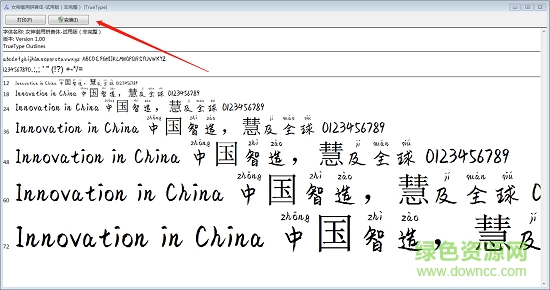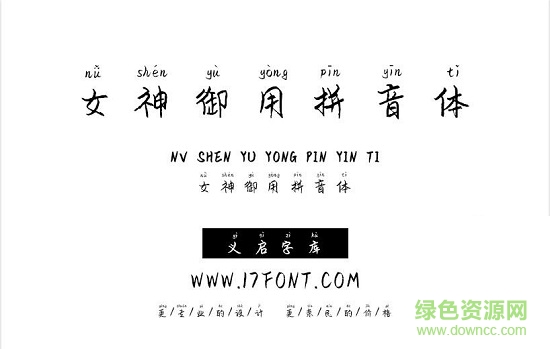
義啟女神御用拼音字體
義啟女神御用拼音體是一款非常注重線條唯美的字體,稱之為女神御用字體,美感是必須的,纖細(xì)的線條設(shè)計(jì)配合完美的比例,讓用戶能夠深深的感受到該字體的美妙之處,喜歡的用戶快來(lái)綠色資源網(wǎng)下載吧!
義啟女神御用拼音體簡(jiǎn)介:
義啟女神御用拼音字體,既然稱為女神,自然有與眾不同的氣質(zhì),那么作為女神,應(yīng)該使用什么字體呢,義啟字庫(kù)正好解決了這個(gè)問(wèn)題,其獨(dú)特的氣質(zhì),可以給人眼前一亮,而且辨識(shí)度也相當(dāng)高,在加上拼音,即便是孩子們,也可以讀出你所編寫(xiě)的所有字。
義啟女神御用拼音字體
義啟女神御用拼音字體特色:
1、每個(gè)字都有自己的拼音;
2、硬筆手寫(xiě)風(fēng)格,彰顯氣質(zhì);
3、筆畫(huà)和間距都恰到好處,堪稱完美。